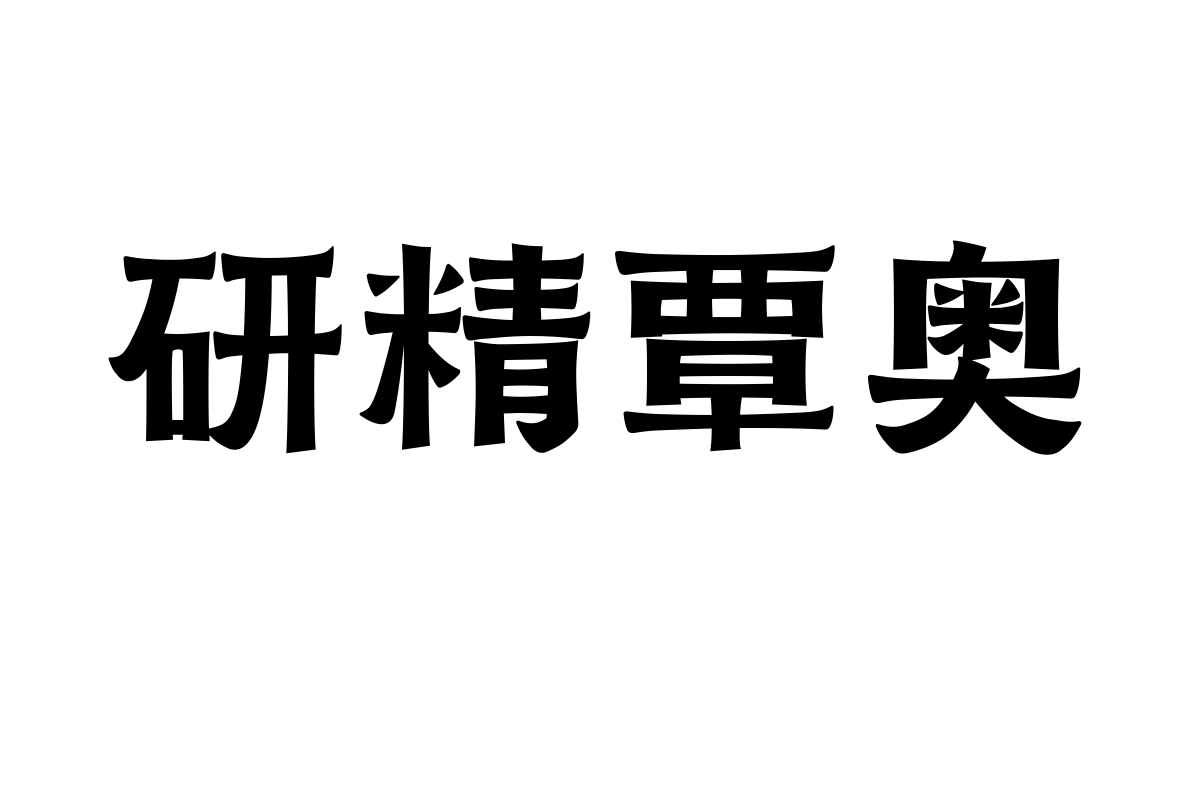
文道润隶体是一款具有独特韵味和艺术风格的字体,它融合了传统书法的精髓与现代设计的理念。这种字体以其独特的笔触、结构和笔画流畅性而受到广泛赞誉。
特点:
1. 笔画流畅:文道润隶体的每一个笔画都经过精心设计,使其呈现出流畅自然的美感。无论是横画还是竖画,都显得自然舒展,仿佛在纸上跳跃。
2. 结构紧凑:该字体的结构紧凑,每个字都显得饱满有力。这使得它在视觉上具有很强的冲击力,能够迅速吸引人们的注意力。
3. 风格独特:文道润隶体的独特之处在于其将传统书法的元素与现代设计相结合。这使得它在保留传统文化韵味的同时,又不失现代感,展现出一种独特的艺术魅力。
4. 适用范围广:无论是用于印刷品、广告、海报还是其他设计作品,文道润隶体都能展现出其独特的魅力。它能够为各种设计元素增添一份古典韵味,使作品更具吸引力。
总之,文道润隶体是一款具有独特韵味和艺术风格的字体,它能够为设计作品增添一份古典韵味,使其更具吸引力。